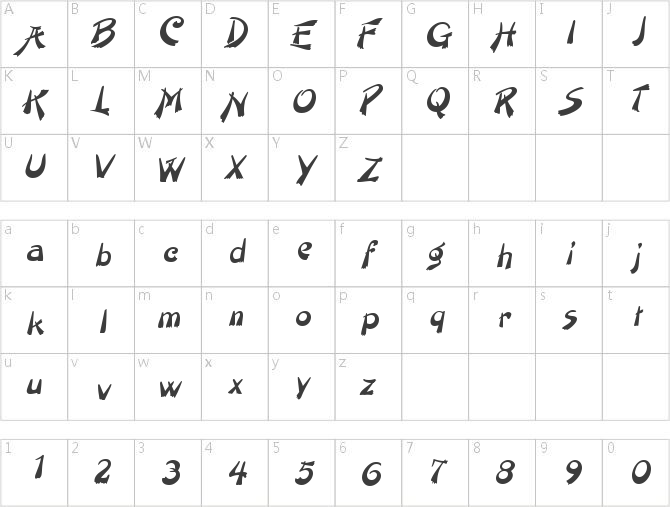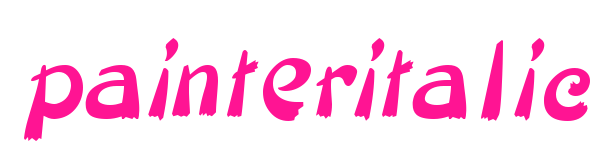
painteritalic 詳情頁
字體名稱: painter
painteritalic
painteritalic字體字庫是一款讓人賞心悅目、百看不厭的英文字體,適合各類廣告和產(chǎn)品包裝設計應用,字體大小0.05MB,格式為ttf字體,上傳用戶是17199970014,作者/版權方為未知